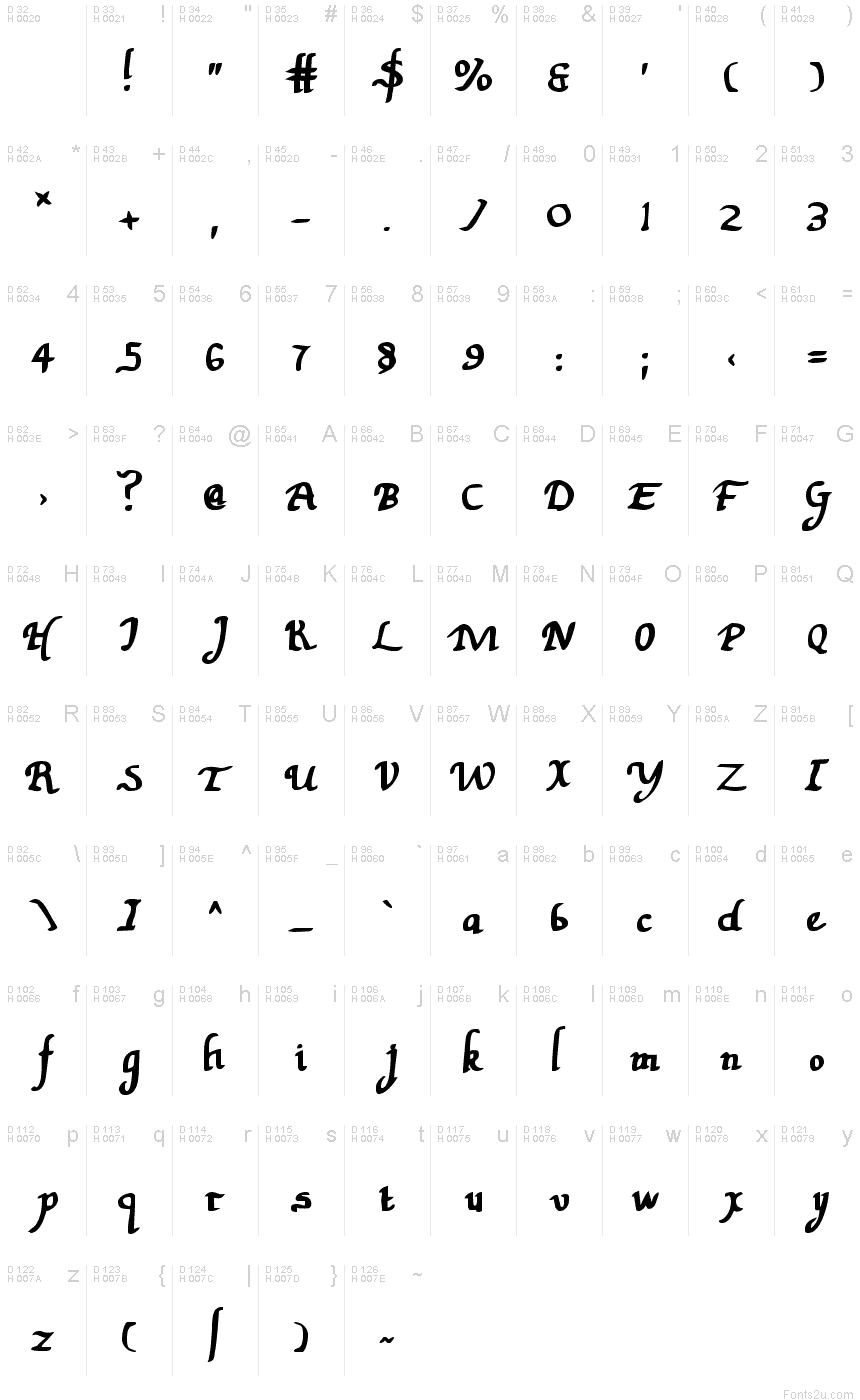
Valley Forge Bold, zaprojektowany przez Iconian Fonts, to darmowy, gruby krój pędzelkowy o szerokich, zatłuszczonych pociągnięciach i ostro ciętych końcówkach. Wysokie, wąskie formy wznoszą się nad zwartymi, zaokrąglonymi literami, a linia porusza się szybkim, malowanym odręcznie zamachem.
Wyrazista sylwetka sprawdza się w brandingach sportowych, opakowaniach restauracyjnych oraz plakatach imprezowych, które wymagają zdecydowanego napisu. Pasuje również do gadżetów i towarów, gdzie duże łuki i spiczaste zakończenia pociągnięć mogą pozostać wyraziste. Dbaj o prostotę otaczających elementów, aby wysokie pociągnięcia i ciasne łączenia nie były stłoczone.